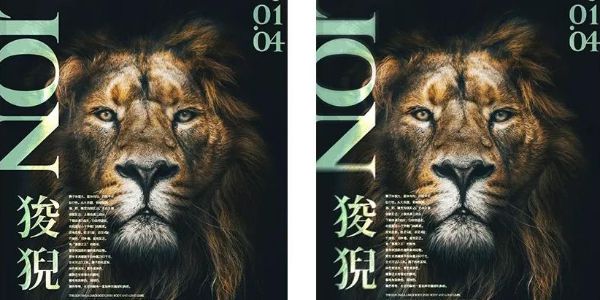
7个文字排版技巧 ,让你的设计潮到起飞(内含小教程)
你是不是在工作中经常遇到这种情况,明明风格、色彩、元素都对了,但还是被客户或老板说,设计不够时尚?
很可能问题就出在文字排版上,今天就来分享几个技巧:
交叉文字色块
在两个或两个以上的长条色块上排一行文字,然后旋转色块使其交叉,效果有点像电影中案发现场的警察封条。
这种排版方式比直接打文字的视觉冲击力更强,又比在平行色块上排文字更有个性,所以常常被用在一些潮牌和综艺的海报、长图中。
文字边框
在画面四周的边界处增加一个矩形边框,形成一个“回”字的效果,然后沿着边框排上一圈文字,最好再搭配一些简单的小图形。
这种把画面包起来的做法,会把原本容易被忽略的边界凸显出来,增强画面的张力,另外生硬的边框和灵活的画面,也可以加强对比,进一步提高视觉冲击力。
字体一般是用比较粗的等线体,如果不想文字太过抢眼,也可以改成描边字。特别要注意边框的大小和颜色,别让边框反客为主。
扭曲文字
如果想把文字排得比较潮,就得对文字进行各种加工处理,比如最近很流行的文字扭曲~
制作扭曲文字,AI里有两个工具,一个是封套扭曲,一个是变形工具。
1.封套扭曲工具
在画板中输入几个文字。
点菜单栏中的对象-封套扭曲-用网格建立。
在网格参数中把行数设为20,列数设为10,然后得到如下效果。
用直接选择工具选中一行锚点,然后用鼠标水平移动一小段。
简单的扭曲效果就做好了。
02.变形工具
输入一个大写的英文单词,并把填充模式改为描边。
把文字拉高变形成下图模样。
在工具面板中选择变形工具,并且双击弹出选项面板,把参数按如下设置。
用变形工具沿着箭头方向拖动。
就得到了如下效果的扭曲文字。
环形文字
把文字沿着一个立体的圆环进行排版,这种处理方式其实是把文字图形化了,在形式上与常规的文字完全区别开来,有很强的空间感。
顺便给大家分享几个在Ai里制作环形文字的工具。
1.封套扭曲
封套扭曲制作环形文字有两种做法,一种是用封套扭曲中的网格建立,把行和列的数值分别设为1和2。
然后手动移动锚点和手柄,使文字形成圆弧形。
用同样的方法完成里层的设计就可以了。
还有一种方法更简单,先画好一个弧形的封闭轮廓,然后把其图层置于文字的上层。
同时选中文字和轮廓图形,执行对象-封套扭曲-用顶层对象建立命令 ,就能得到如下效果。
运用相同的方法制作里层效果。
这种方法虽然快捷,但是制作的效果容易出现破裂或者有瑕疵的情况,所以,要根据实际情况对轮廓图形进行调整。
2.3D贴图
在画板上输入一组文字,并镜像复制一组,转曲合并在一起,效果如下。
在顶部菜单栏选择窗口-符号,打开符号面板。
在符号面板中点击右下角下载新建符号图标,然后点击确定,刚刚排列的这组文字就可以用作贴图素材了。
接下来我们要画一个圆柱,首先画一个矩形,并删掉它的左“边”。
执行窗口中的3D命令,把旋转参数中间的数值改为0,其他保持默认,然后点亮左下角的预览,一个圆柱就画好了,不过到这里还不能点确定。
点击左下角的“贴图”命令进入贴图面板,点击右上角“表面”设置栏右边的三角形,把贴图面翻制3/3,贴图的面就变成了圆柱的弧面,如下图所示。
然后再点出左上角的“符号”的下拉菜单,选择刚刚新建的弧形文字符号。
分别点选缩放以适合、三维模型不可见、预览按钮,就得到了如下效果。
把图形删格化,并把里层填充为灰色,一组圆环字的设计就做好了。
这种效果是最标准的,但是最两侧的文字识别性会比较低。
故障风标题
别看故障风流行了几年,但故障文字依然很热,在各类时尚海报中都常见其踪影。
比较简单的做法是在白色文字层的基础上,复制出两层分别填充蓝色和玫红色,并将其置于底层,然后分别对蓝色和红色文字层执行风格化-大风滤镜。
除此之外也可以画一些小线条与文字层做合并和剪切处理,这样制作出来的故障效果更细致。
手写体字叠图
说到潮的字体,我们很容易想到笔画简单、硬朗的字体,其实手写字体也可以排得很潮,豪放的手写字体搭配亮丽的色彩,然后压在图片上,既时尚又很有动感。
重复
重复是平面构成中的一种很经典的形式,近几年在文字排版中也很流行,通常的用法是提炼出设计中的一个关键词,并使用比较大的字号,然后把它复制数组,进行重复排列。
还可以把文字的形态改为描边字,效果会更精致、优雅一些。
另外,把重复的的文字做渐变裁剪效果,也是很流行的一种处理方式。